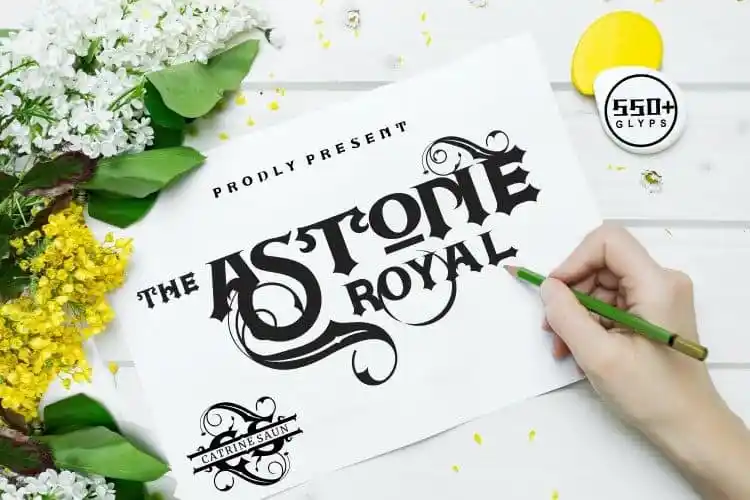
Astone Royal Blackletter Font – Download Grátis
Aston Royal Blackletter é uma nova fonte moderna e encantadora lançada recentemente pela artype07. Este design foi inspirado por várias letras e seu resultado final é uma fonte de estilo blackletter, cheia de belas curvas. Esta fonte traz uma versatilidade única com cada letra possuindo entre oito e dezessete variações diferentes. Isso garante que qualquer projeto seja apresentado com um toque moderno e elegante, sem perder a essência do estilo blackletter. Ideal para gráficos em alta qualidade ou designs digitais, Aston Royal Blackletter é perfeito para quem busca uma fonte única que se destaca no ambiente da arte digital. Seja você designer de software, profissional de marketing ou criativo do mundo da moda, este novo lançamento da artype07 é certamente uma escolha interessante para o seu próximo projeto.